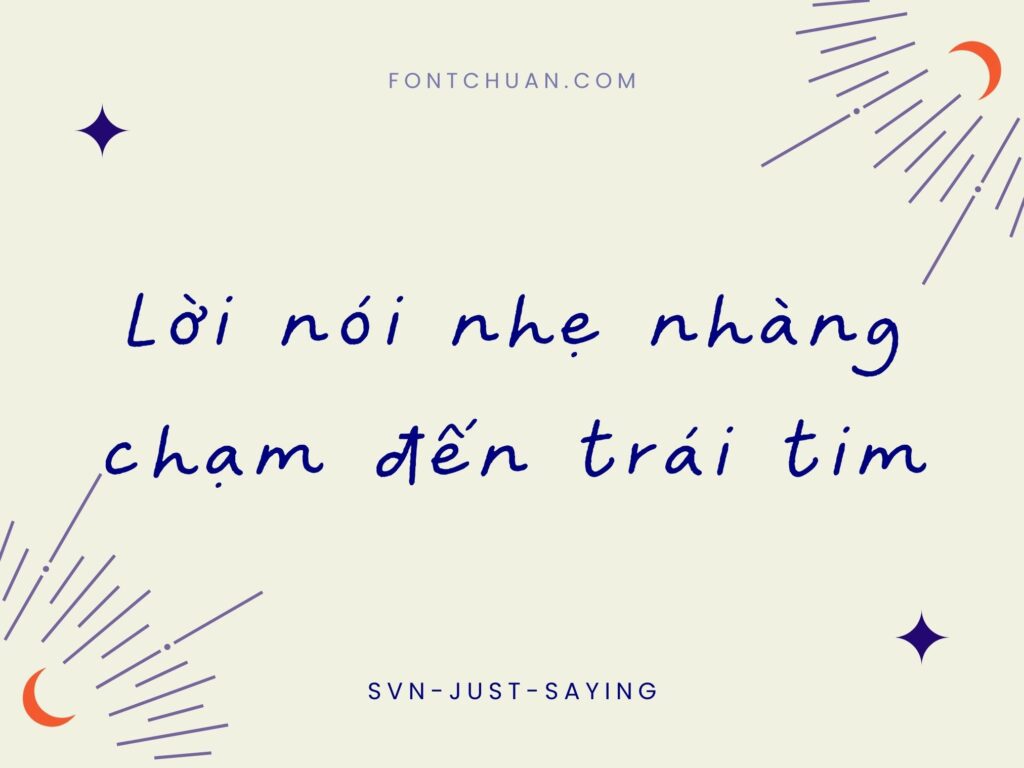
Font SVN Just Saying Việt Hóa
Tác giả Font: Nicky Laatz
Font SVN Just Saying là phiên bản Việt hóa của kiểu chữ Just Saying, được thực hiện bởi STYLEno.1 Fonts. Just Saying là một font chữ viết tay ngọt ngào, đi kèm với bộ dingbats chứa các hình vẽ nhỏ xinh xắn, giúp thiết kế của bạn thêm phần lấp lánh. Font này bao gồm 6 biến thể với độ đậm và độ nghiêng khác nhau, cho phép bạn lựa chọn phù hợp với dự án của mình. Just Saying lý tưởng cho các trích dẫn nổi bật, ghi chú viết tay, thiệp chúc mừng dễ thương và đặc biệt là tạo dấu ấn thương hiệu.
SVN Just Saying phù hợp cho các thiết kế như thiệp mời, logo thương hiệu, tiêu đề, bao bì sản phẩm và các ấn phẩm truyền thông. Các ngành nghề như thiệp cưới, giáo dục và ẩm thực có thể tận dụng font này để tạo điểm nhấn trong thiết kế. Ngoài ra, font cũng thích hợp cho các sự kiện như Valentine, Sinh nhật, Tết và các lễ hội khác.